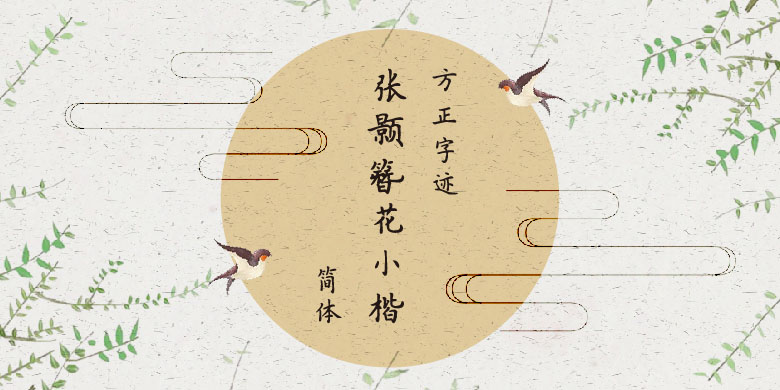
品牌:方正字迹设计师:张颢发行时间:2018字库编码:大陆简体(GB2312-80)、简繁扩展(GBK)分类:常规书写·硬笔
簪花小楷相传由“书圣”王羲之师卫夫人所创。首都师范大学中国书法文化研究院张颢博士据其书法风格特点,创作出“当代簪花小楷”繁简字体。其状若簪花,雅致娟丽,秀美灵动,飘逸出尘。重现簪花之风采,一经推出便深受广大书法爱好者青睐,是楷书临习范本的不二之选。
方正字迹-张颢簪花小楷是一款非常漂亮的艺术字体,字体看上去非常的灵动、飘逸,它的形状若簪花,雅致娟丽,适合应用于艺术设计、广告宣传设计、网页信息展示、书法字帖等,广泛用于各种书刊、画册的设计、报纸和杂志和书籍等领域。